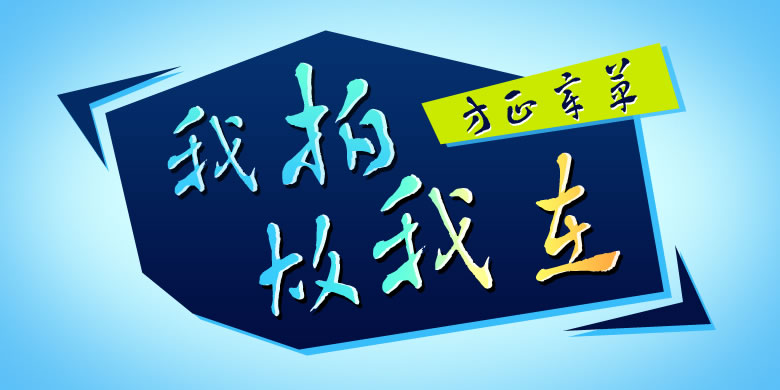
由中国书法家协会会员、国家级一级美术师卫高潮创作。卫高潮,1958年生于陕西,1980年从师吴三大,1985年加入中国书法家协会,2009年被评为国家一级美术师,现为陕西省书协副主席,已出版《卫高潮真草墨迹》、《卫高潮章草书作》等书法著作。章草,是书法的传统书体之一。是早期的草书,始于汉代,由草写的隶书演变而成。章草是“今草”的前身,与“今草”的区别主要是保留隶书笔法的形迹,上下字独立而不连写。方正章草体行笔劲健,古雅沉雄,缓涩凝重,浑穆丰茂,敦厚朴实,不激不厉;构架骨气通达,宽博疏朗,行次阔绰而气韵贯通,让人感觉灵动而富有韵律。